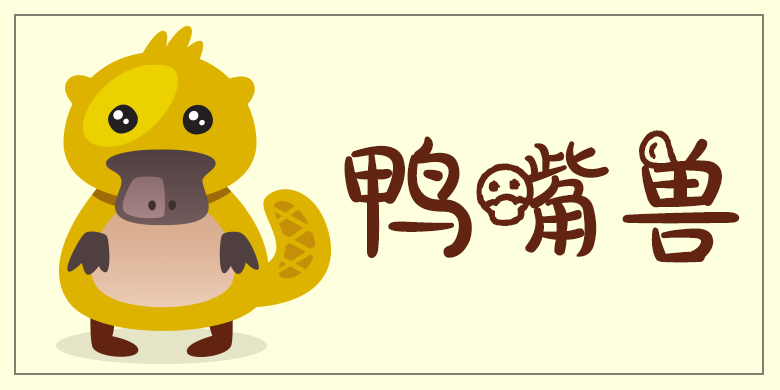
品牌:方正手迹设计师:范雅琼,李潇发行时间:2019字库编码:大陆简体(GB2312-80)分类:创意书写字体属性:精品字
鸭嘴兽这款字,其文字结构灵活,笔画错落有致,打破了许多固有的排列模式。这款字体手写风格鲜明,笔形圆融浑穆,个性清新萌动,适用于儿童类品牌的广告和产品包装设计。
品牌:方正手迹设计师:范雅琼,李潇发行时间:2019字库编码:大陆简体(GB2312-80)分类:创意书写字体属性:精品字
鸭嘴兽这款字,其文字结构灵活,笔画错落有致,打破了许多固有的排列模式。这款字体手写风格鲜明,笔形圆融浑穆,个性清新萌动,适用于儿童类品牌的广告和产品包装设计。